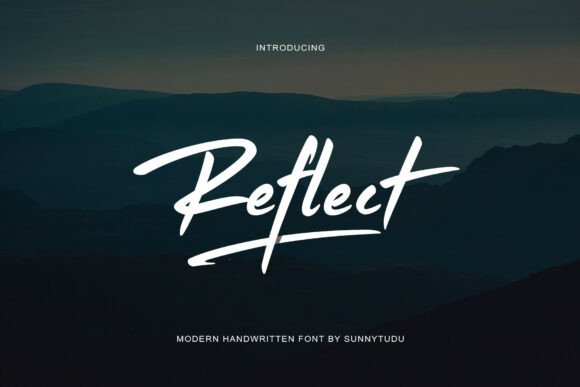
Reflect Handwritten Font
Если вы ищете высококачественные ресурсы, такие как Reflect Handwritten Font, этот премиум-пакет — фантастический выбор для ваших творческих проектов.
Созданный с высокой точностью, Reflect Handwritten Font предоставляет чистые векторы, плавную типографику и коммерческую лицензию для вашего спокойствия.